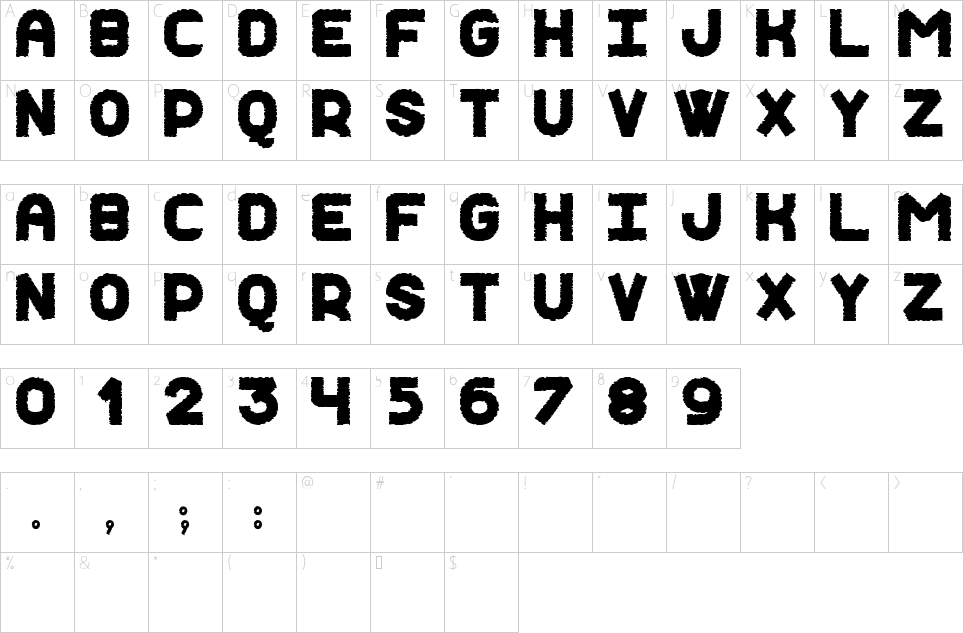
A fonte “Destroyed New St” é uma criação de Southype que oferece um estilo único e desafiador para designers e criadores de conteúdo. Inspirada na devastação moderna, esta fonte traz uma intensidade visual que pode transformar qualquer projeto em algo profundo e emocionante. Com seu design cuidadosamente desenvolvido por um talentoso designer gráfico desconhecido, a “Destroyed New St” tem sido baixada pelo público cerca de 11.426 vezes. Este download gratuito é uma excelente oportunidade para adicionar esse estilo único à sua arsenal de fontes e dar vida a qualquer texto que você criar. Seja em seu próximo projeto gráfico ou design web, “Destroyed New St” pode fornecer um ponto de partida incrivelmente dinâmico e vibrante.